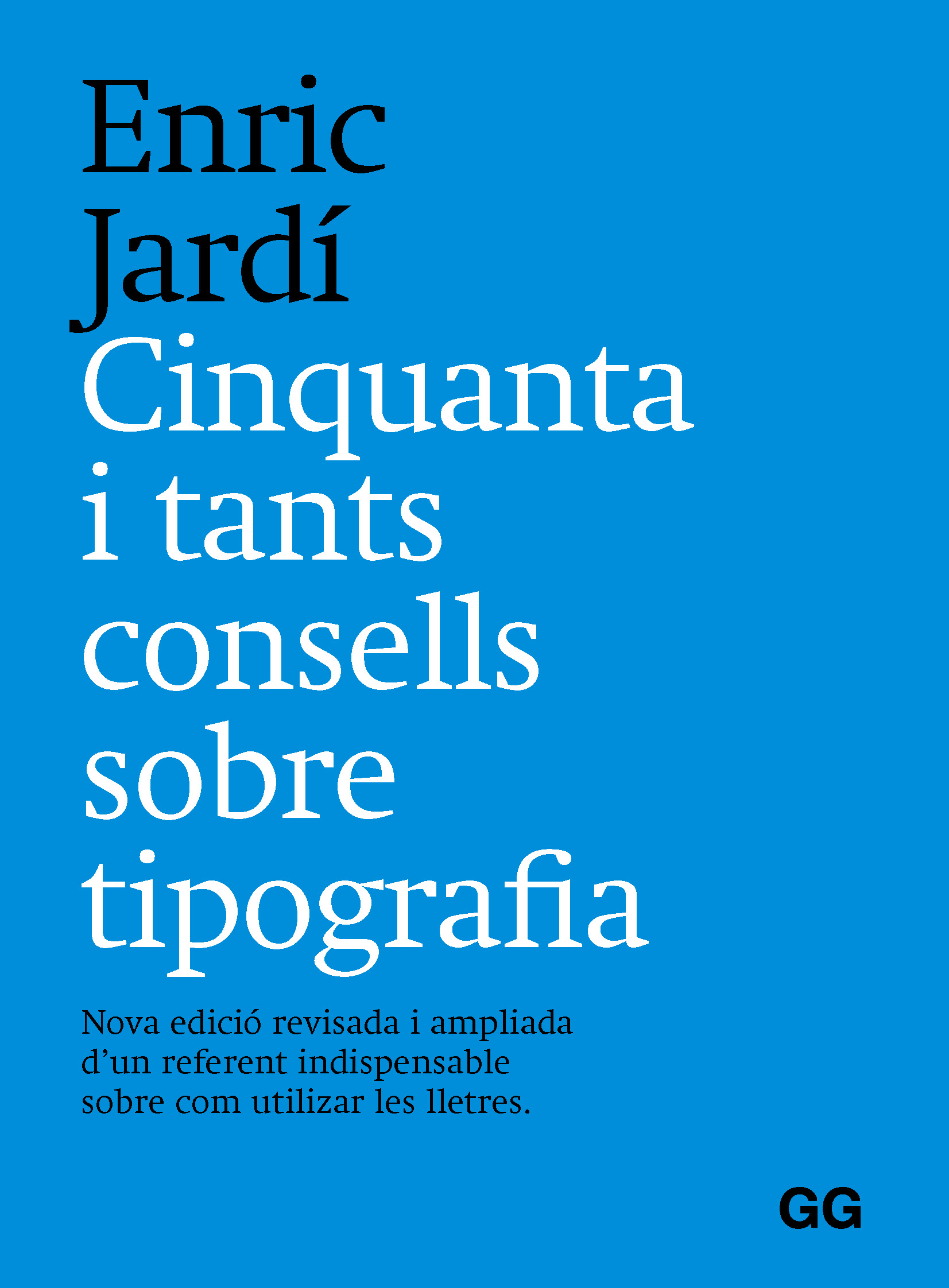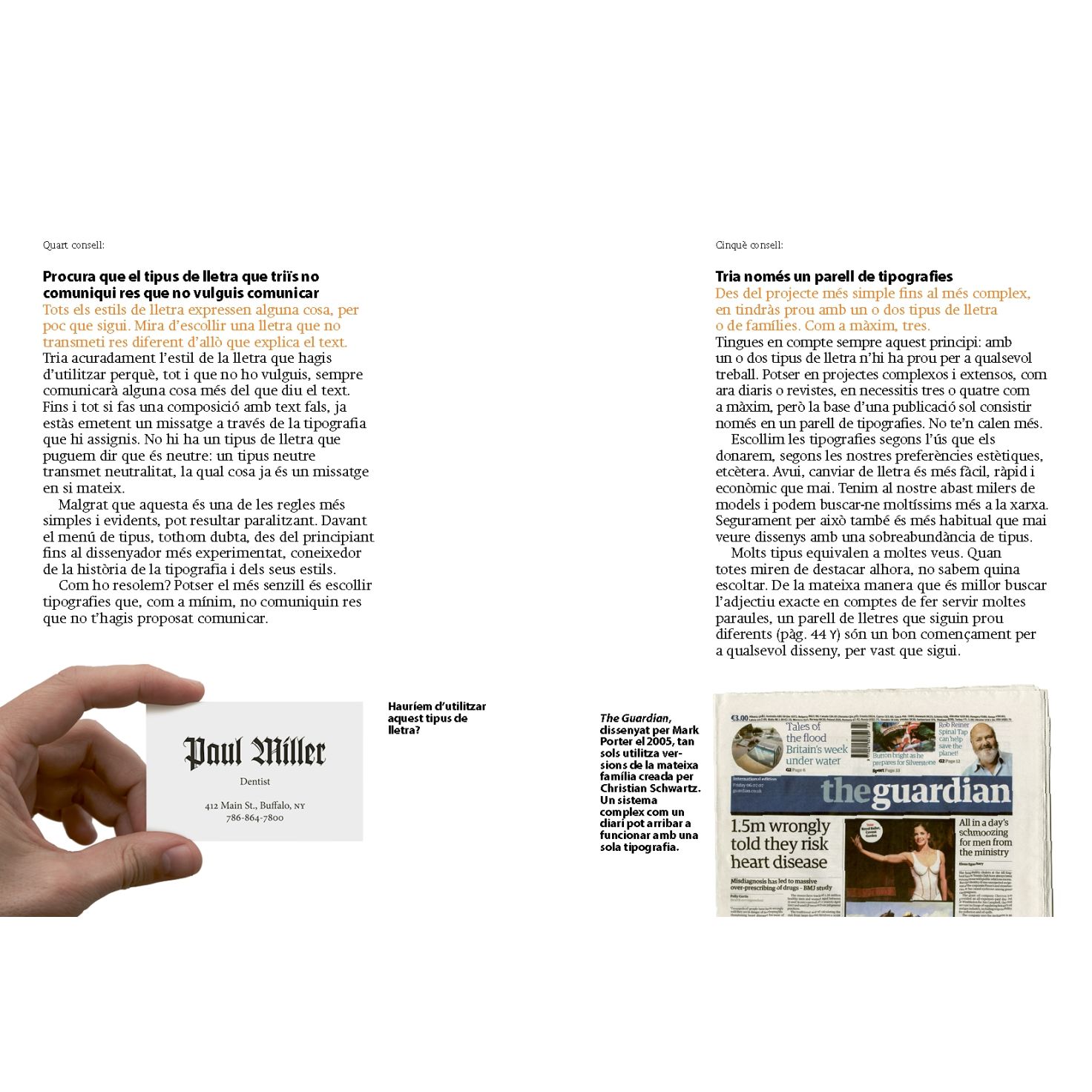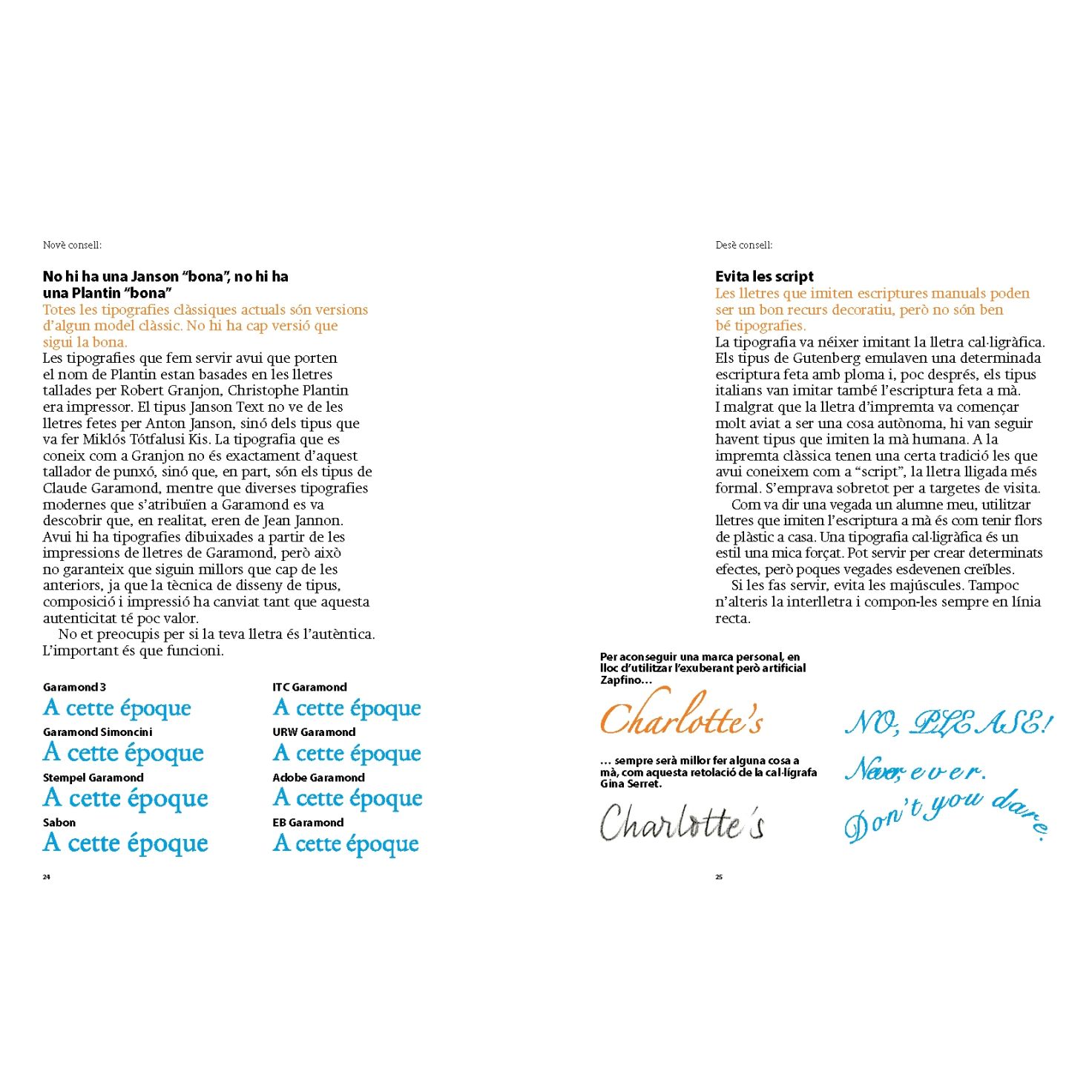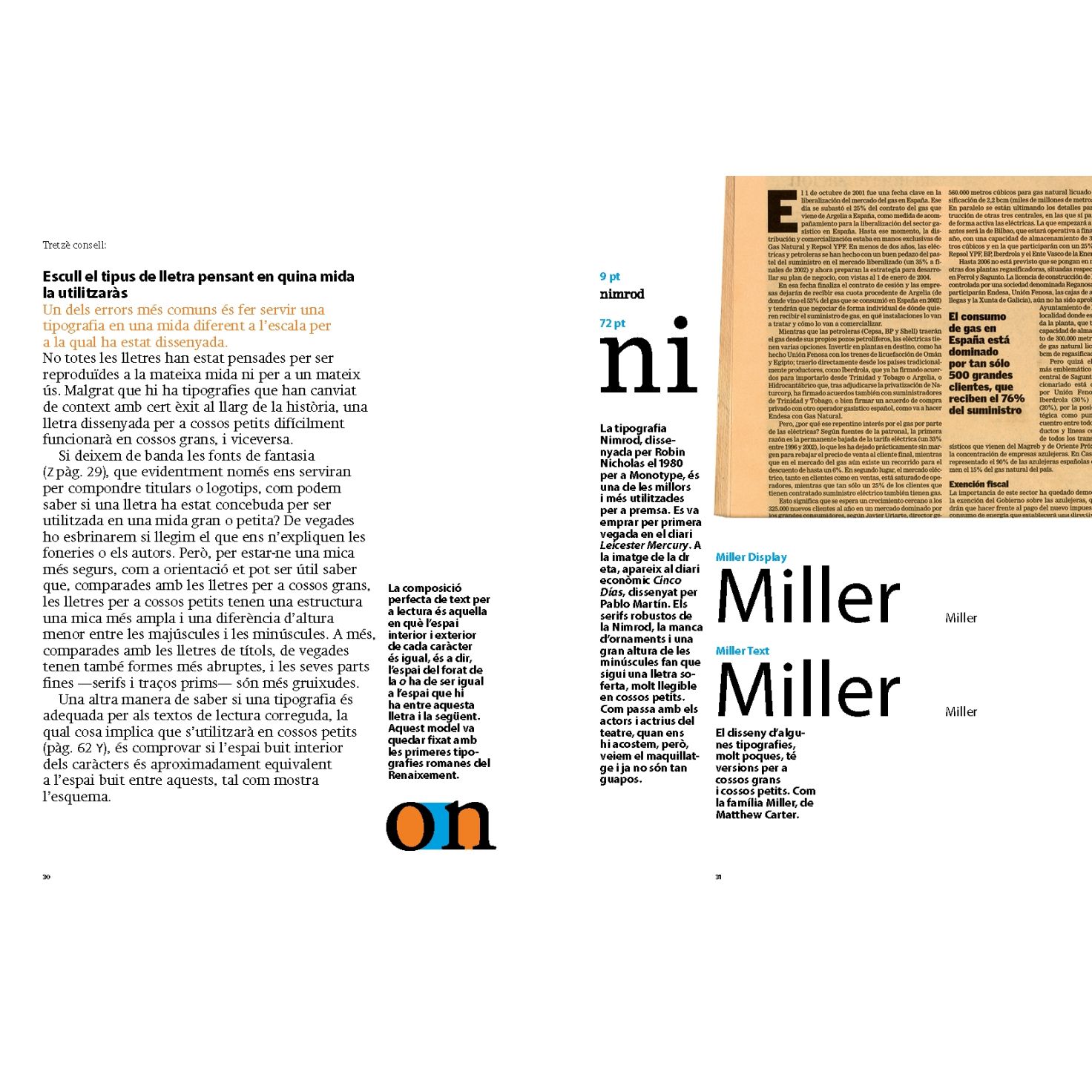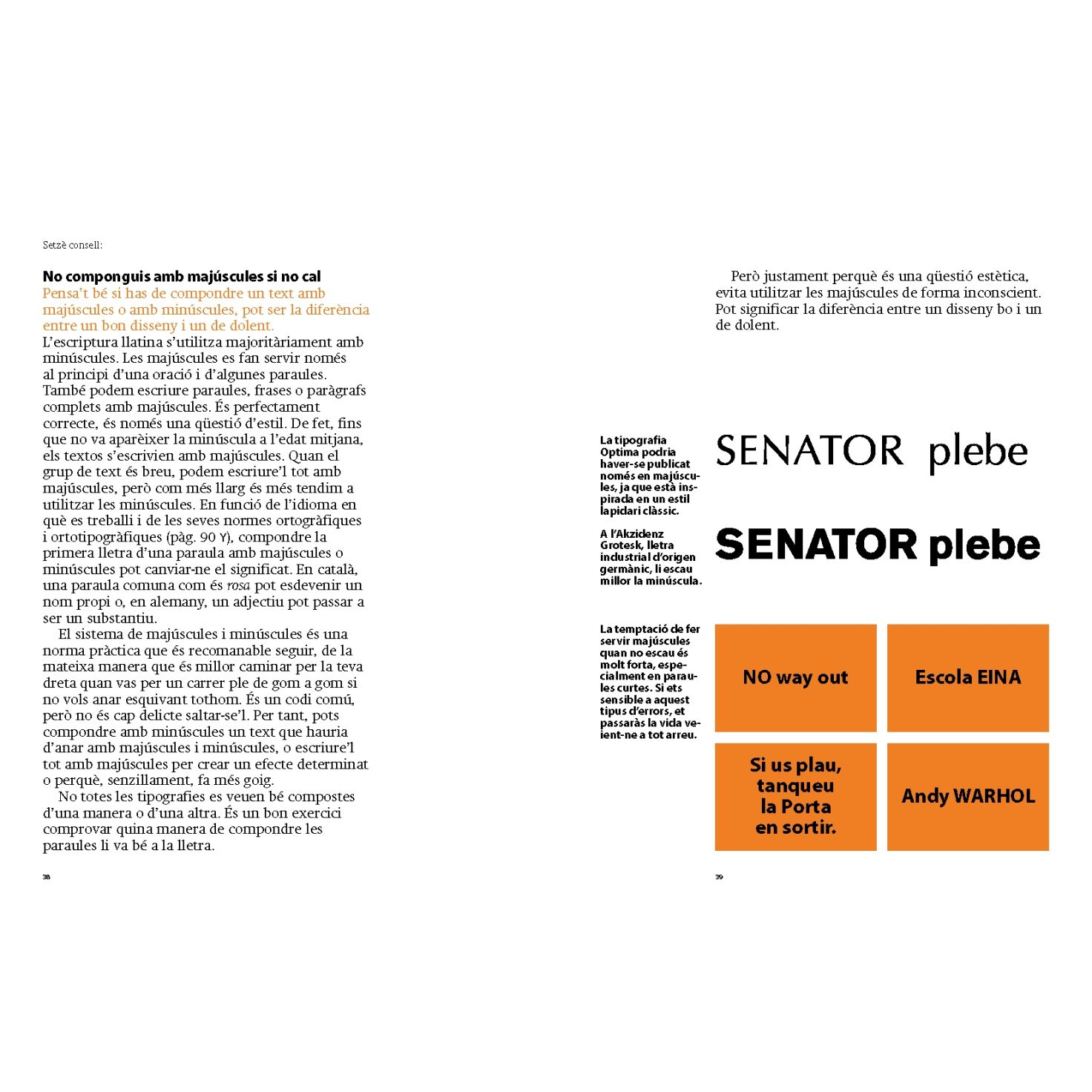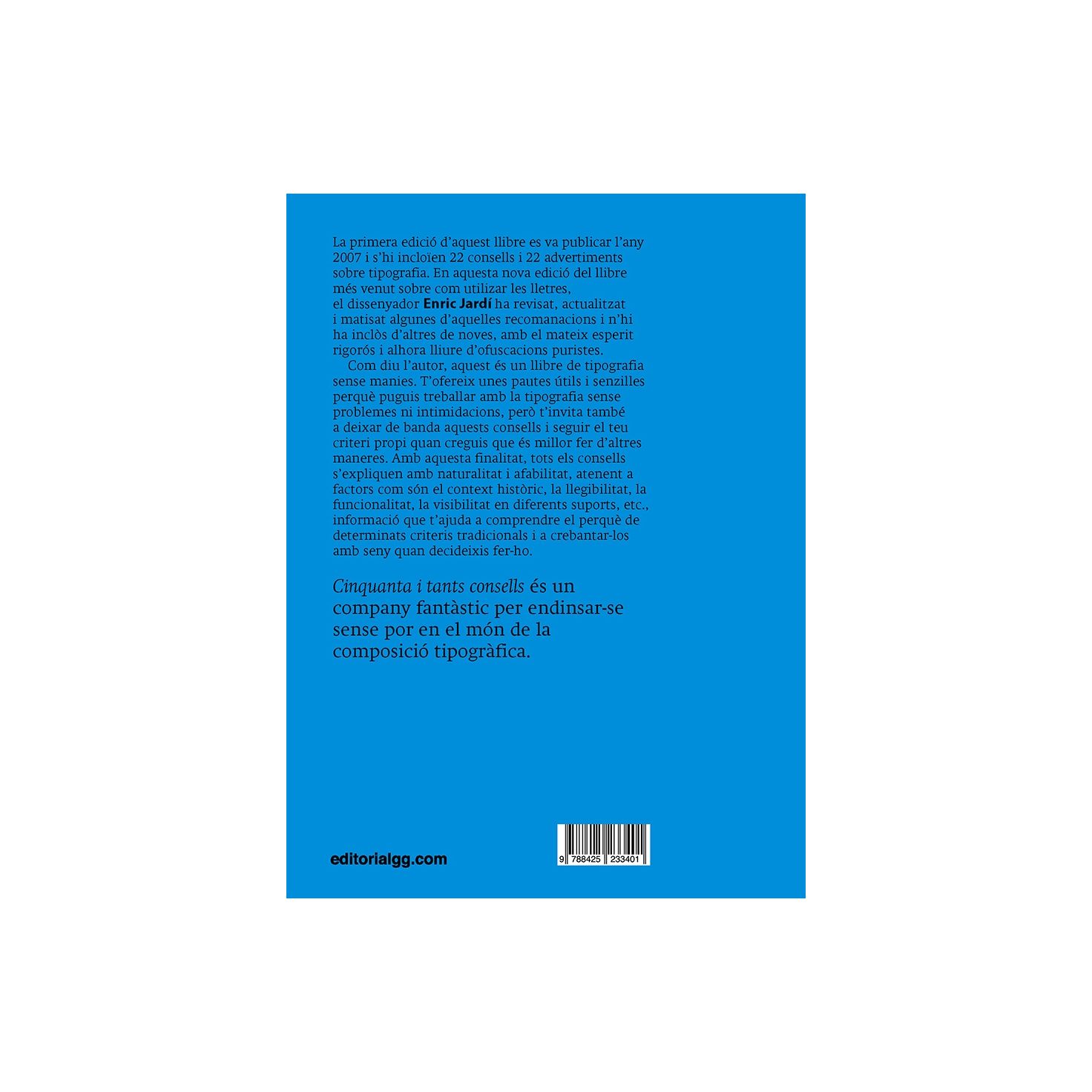
Cinquanta i tants consells sobre tipografia
Nova edició revisada i ampliada d’un referent indispensable sobre com utilizar les lletres.
La primera edició d’aquest llibre es va publicar l’any 2007 i s’hi incloïen 22 consells i 22 advertiments sobre tipografia. En aquesta nova edició del llibre més venut sobre com utilizar les lletres, el dissenyador Enric Jardí ha revisat, actualitzat i matisat algunes d’aquelles recomanacions i n’hi ha inclòs d’altres de noves, amb el mateix esperit rigorós i alhora lliure d’ofuscacions puristes.
Com diu l’autor, aquest és un llibre de tipografia sense manies. T’ofereix unes pautes útils i senzilles perquè puguis treballar amb la tipografia sense problemes ni intimidacions, però t’invita també a deixar de banda aquests consells i seguir el teu criteri propi quan creguis que és millor fer d’altres maneres. Amb aquesta finalitat, tots els consells s’expliquen amb naturalitat i afabilitat, atenent a factors com són el context històric, la llegibilitat, la funcionalitat, la visibilitat en diferents suports, etc., informació que t’ajuda a comprendre el perquè de determinats criteris tradicionals i a crebantar-los amb seny quan decideixis fer-ho.
Cinquanta i tants consells és un company fantàstic per endinsar-se sense por en el món de la composició tipogràfica.
ÍNDEX
Introducció
No cal que t’aprenguis com es diuen totes les parts de la lletra
Totes les tipografies es llegeixen bé
Classifica les tipografies com et sembli millor
Procura que el tipus de lletra que triïs no comuniqui res que no vulguis comunicar
Tria només un parell de tipografies
No t’equivoquis de mitjà
No utilitzis succedanis
No recreïs estils històrics
No hi ha una Janson “bona”, no hi ha una Plantin “bona”
Evita les script
Rebutja els tipus amb caràcters capritxosos
No triïs lletres temàtiques
Escull el tipus de lletra pensant en quina mida la utilitzaràs
Utilitza tipus que estiguin dissenyats per al teu idioma
Retoca les paraules soltes
No componguis amb majúscules si no cal
Si és imperceptible, pots condensar i expandir les lletres
No intentis convertir la lletra en una imatge, la lletra ja és una imatge
Assegura’t que el teu tipus arriba fins al final
No inclinis lletres a l’esquerra ni componguis en vertical lletres horitzontals
No posis juntes dues lletres que s’assemblin massa
No componguis junts pesos amb diferents graus de condensació
Iguala les mides de lletra quan posis junts dos tipus diferents
Pots deixar espai addicional entre les majúscules
No afegeixis espai addicional entre les minúscules
No facis massa categories
No toquis massa els valors per defecte
Si et deixen, compon a caixa esquerra
Convida a la lectura
Segur que et cal una retícula?
Oblida el cícero, les piques i els punts
Fes marges regulars
No facis línies massa llargues ni massa curtes
No t’escarrassis amb el número de pàgina
Marca els paràgrafs convenientment
No combinis columnes centrades amb d’altres no centrades
Iguala el nombre de línies de les columnes
No deixis paraules soltes
No construeixis sistemes d’organització del text que no siguin intuïtius
Quadra les línies de text
Tanca l’interlineat i la interlletra amb els cossos grans
Si compons amb majúscules, tanca la interlínia
Augmenta la interlínia quan construeixis paràgrafs en negatiu
Oblida’t del kerning
Tria amb cura els caràcters
Tingues cura dels números
Evita segons quines lligadures
No utilitzis falses negretes, falses cursives ni falses versaletes
Les negretes són per destacar paraules
Evita les negretes de les romanes
El paper i la pantalla fan efectes diferents
Escull bons tipus per a pantalla i aplica’ls el valor de cos adequat
Quan hagis de justificar columnes de text, examina bé la partició i l’espaiat